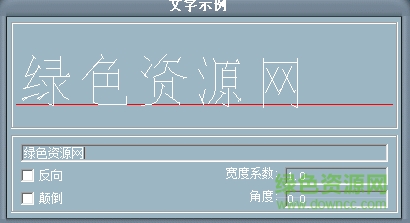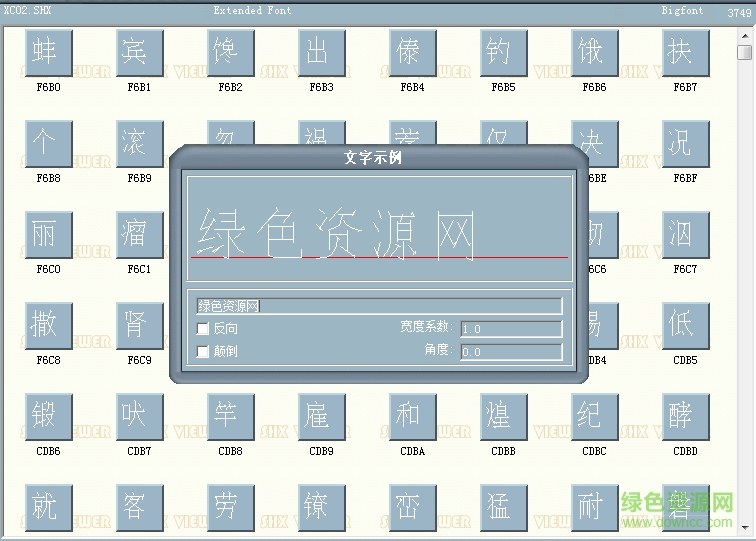
xc02.shx字體是autocad中必不可少的一款字體,該字體以漢字為主,字體非常的端正大方,并且結(jié)構(gòu)簡(jiǎn)潔,筆畫(huà)纖細(xì),非常適合用于設(shè)計(jì),感興趣的朋友歡迎下載使用??!
xc02.shx字體是一款非常美觀的cad字體應(yīng)用,以進(jìn)行中英文和阿拉伯?dāng)?shù)字的常規(guī)書(shū)寫(xiě),字體婉約流暢,筆畫(huà)纖細(xì),使用起來(lái)非常的方便!